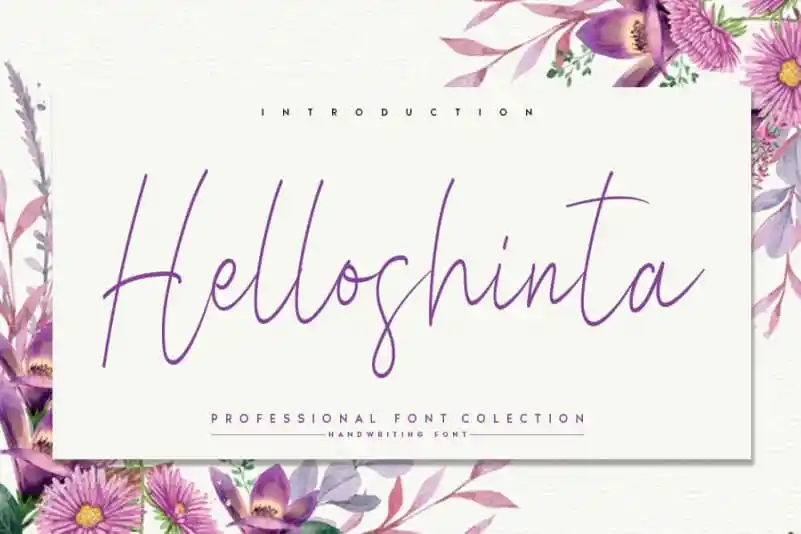
A Helloshinta Handwritten Font é uma escolha perfeita para aqueles que valorizam a autenticidade do grafismo à mão enquanto admitem os tempos atuais. Ela preserva as influências clássicas e refinadas da calligrafia, mas não se limita ao passado; simboliza também um toque moderno e atual. Esta fonte é perfeita para adicionar uma personalidade única aos seus trabalhos de design gráfico, seja em editoriais, identidades corporativas ou até mesmo como detalhes de texto no design web. Adquira-a agora e elevie seu projeto a outro nível.